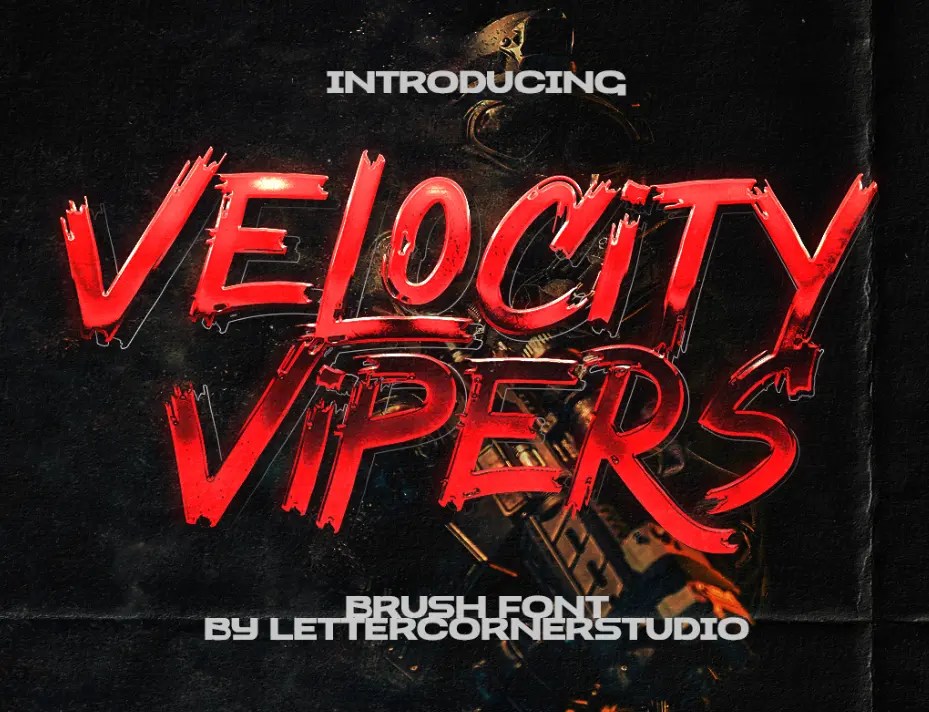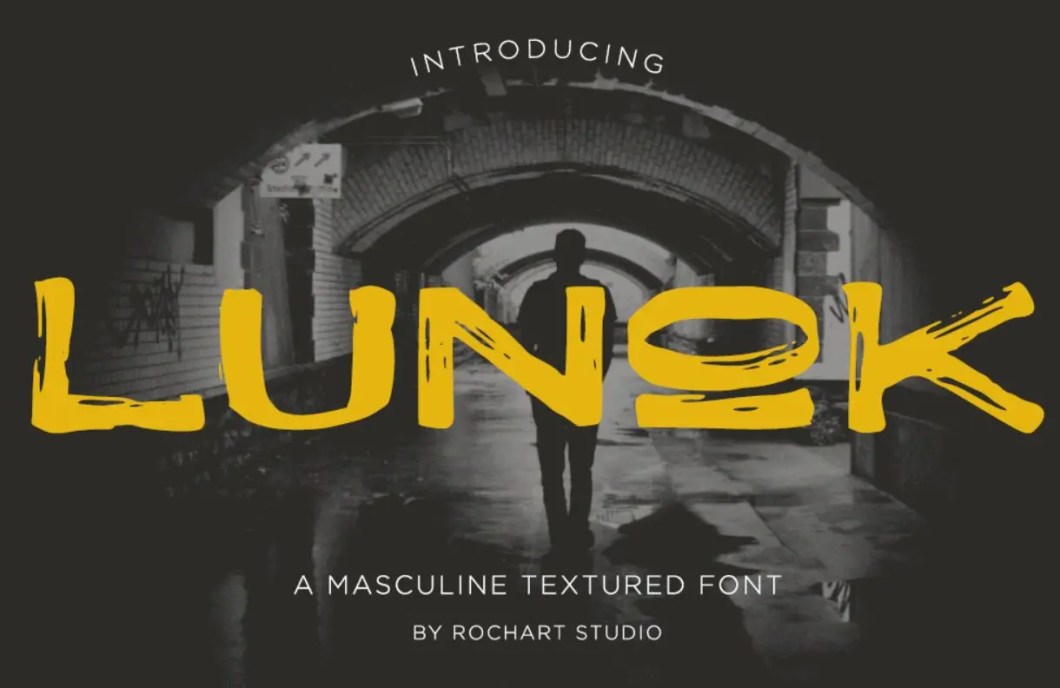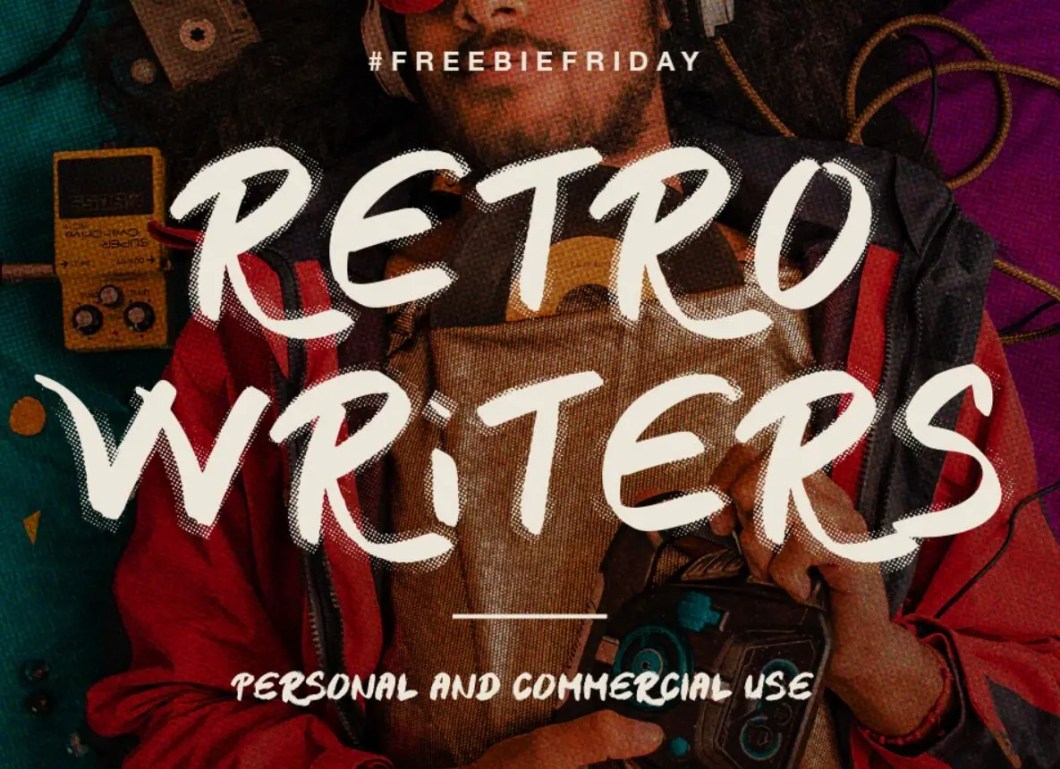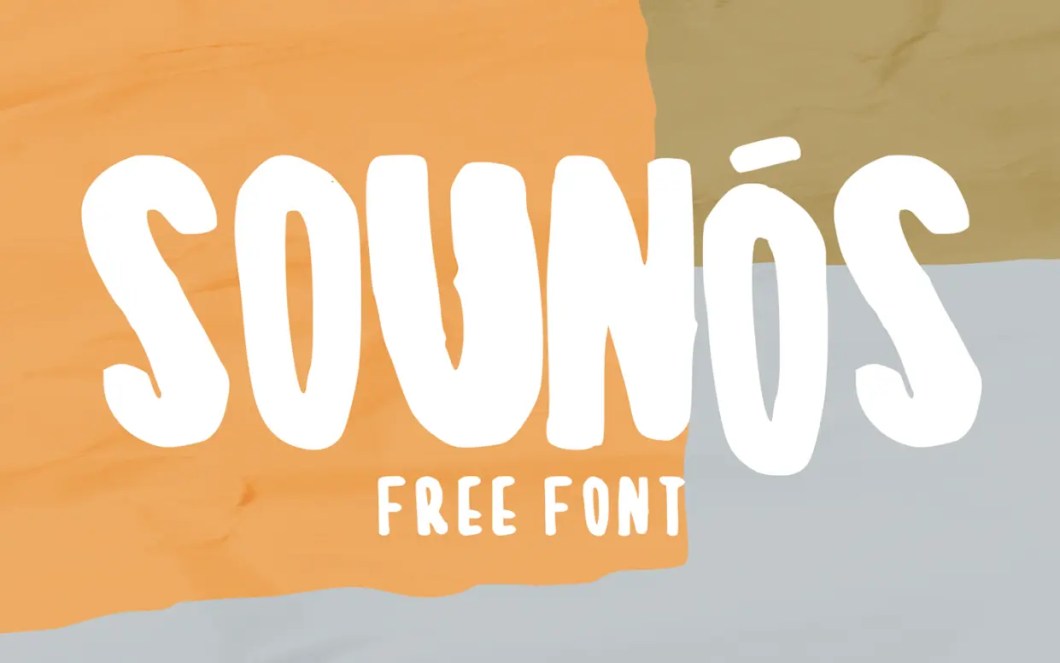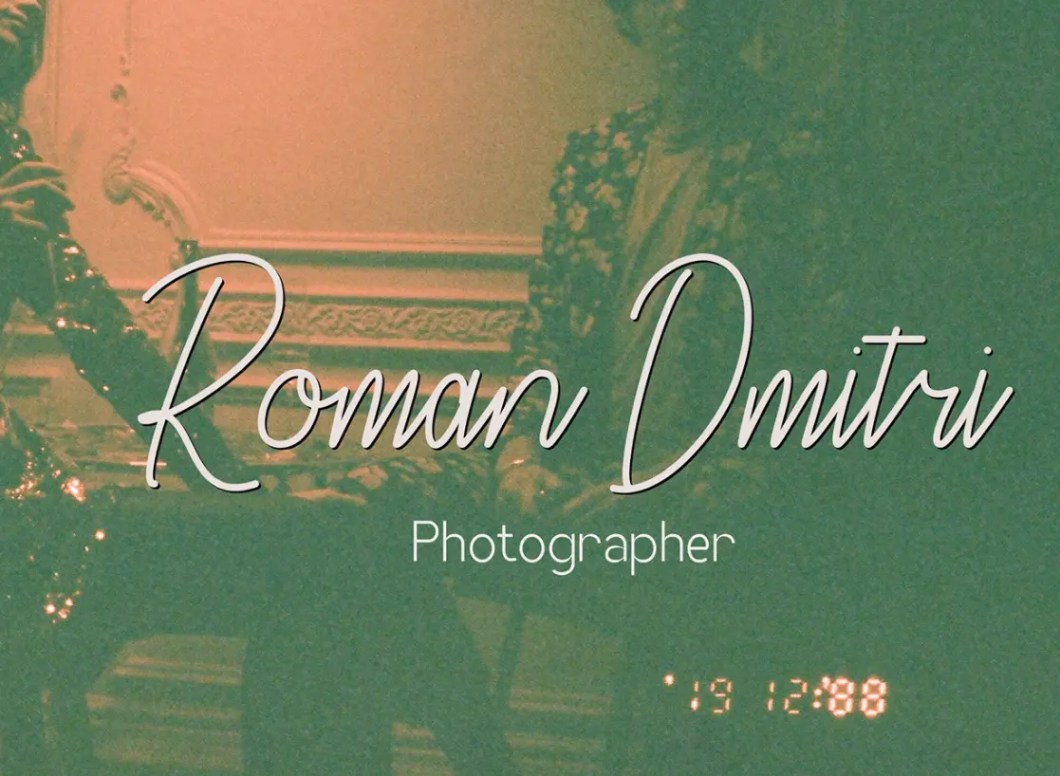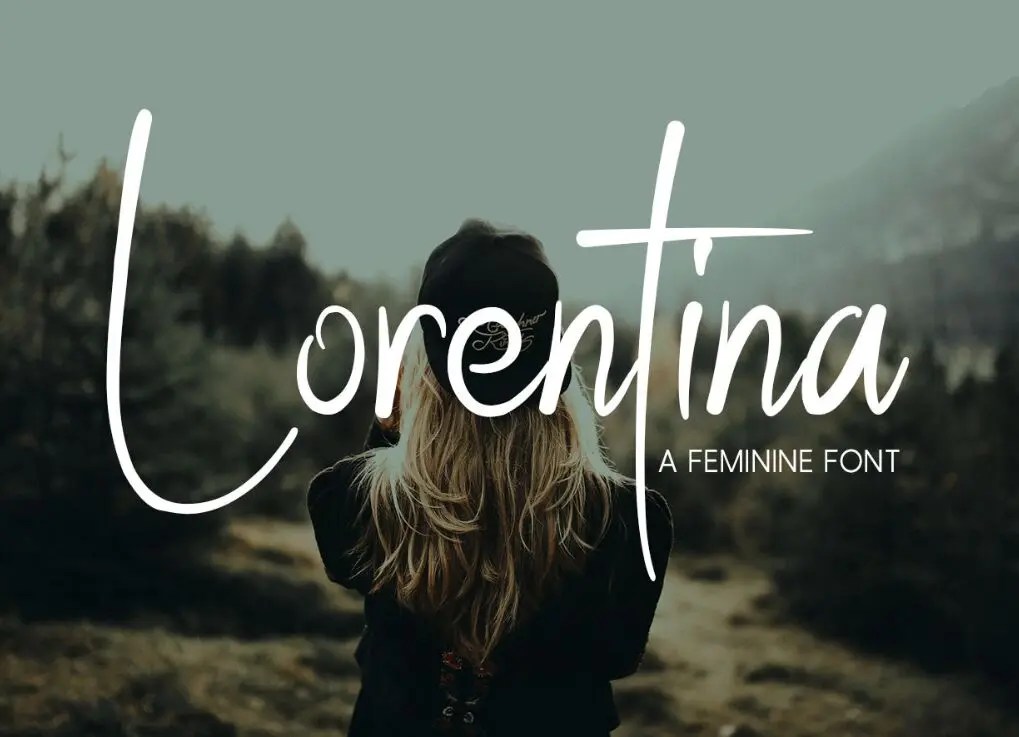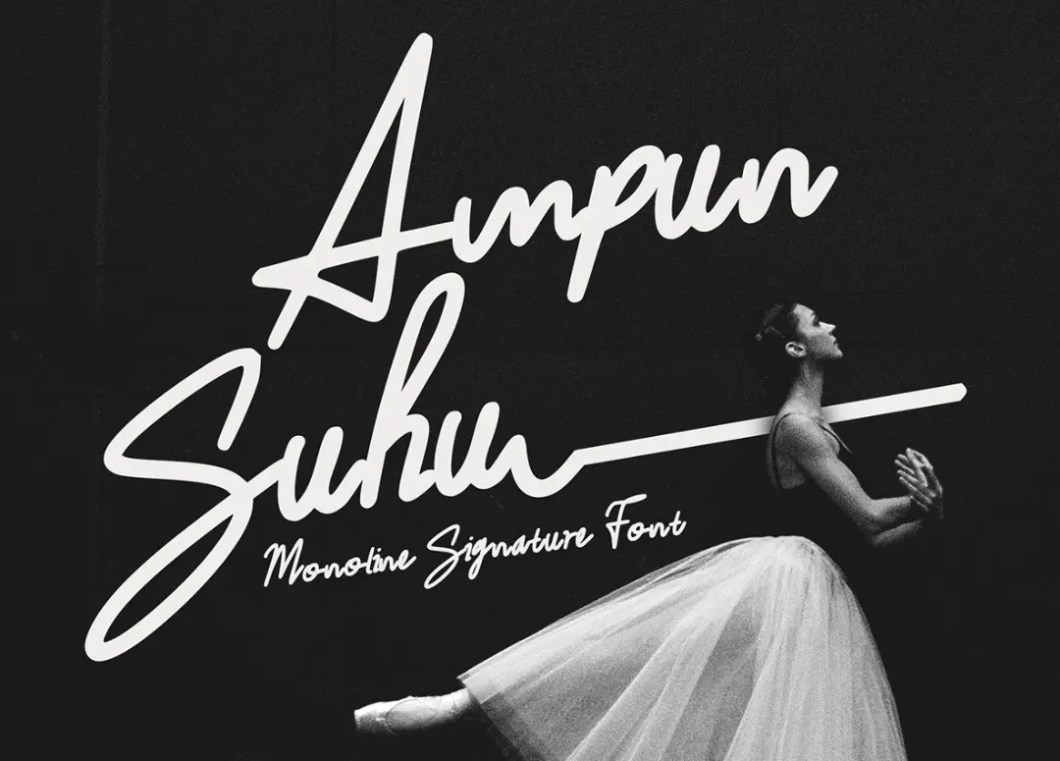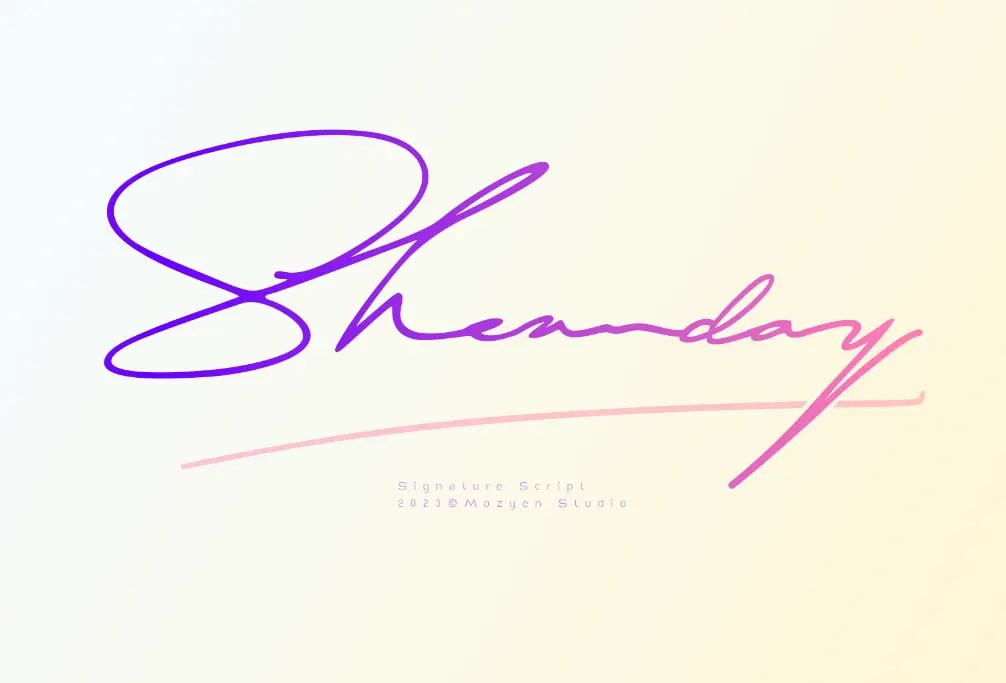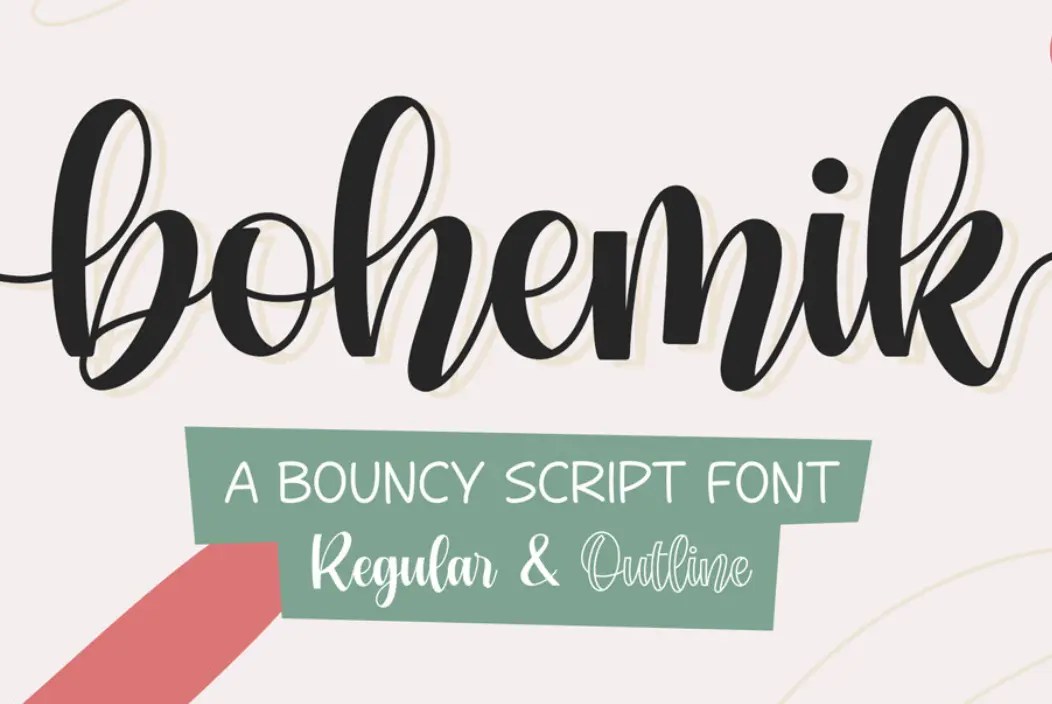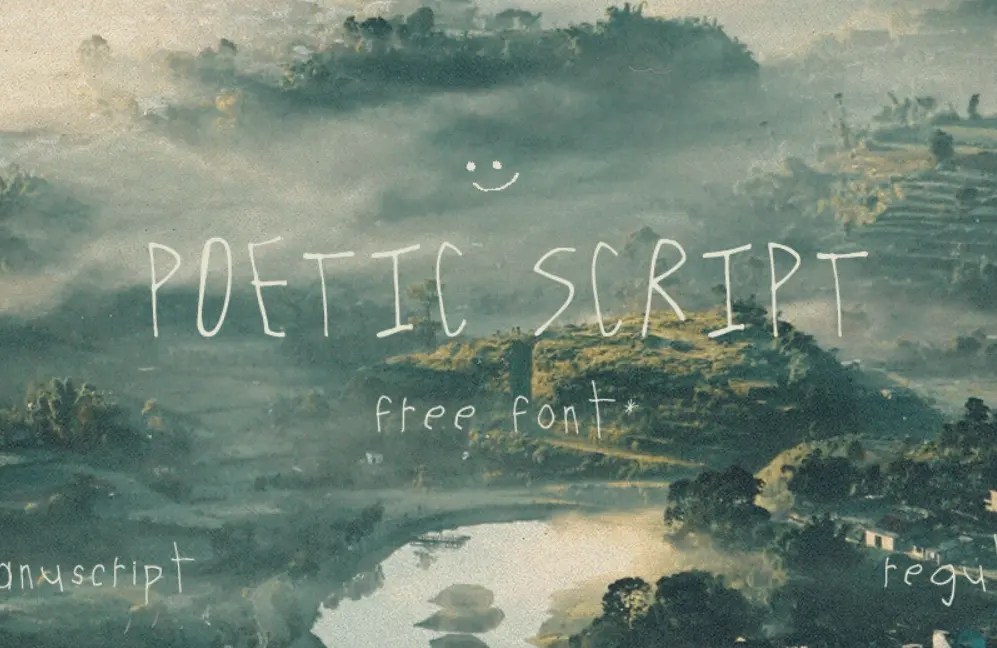
80+ beste Brush/Script/Calligraphy/Signature Fonts für modernes Grafikdesign
Die Brush Script-Schriftart ist eine äußerst vielseitige Schriftart, die in zahlreichen Designprojekten Anwendung findet. Mit einer reichen Geschichte, die bis zu ihrer Einführung im Jahr 1942 durch den amerikanischen Schriftenentwerfer Robert E. Smith zurückreicht, erlangte die Brush Script in den 1960er Jahren immense Popularität und wurde zu einem festen Bestandteil von Werbung und Promotionmaterialien der Nachkriegszeit.
Bekannte Logos, die diese Schriftart verwenden, sind möglicherweise im „The Price is Right“-Spiel in der „One Away“-Runde, im ursprünglichen Logo der Jerry Springer Show und im Logo von Virtua Fighter zu finden.
Obwohl diese Art von Schrift in Logos möglicherweise nicht so häufig vorkommt, ist sie eine der am häufigsten verwendeten Schriftarten für informelle Skripte. Ihre weitverbreitete Verwendung im Webdesign wird auf ihre Beliebtheit, Lesbarkeit und nostalgische Ästhetik zurückgeführt.
Der Vintage-Charme von Brush Script liegt in seinem handgeschriebenen, informellen Stil – eine Abkehr von den digitalen Schriftarten, die in der heutigen Designlandschaft vorherrschen. In einer Ära, die von digitalen Werkzeugen dominiert wird, wird der Reiz einer Schrift, die an handgefertigte Federn, Kalligrafie und Malerei erinnert, zunehmend geschätzt.
Die Wiederbelebung von Brush Script-Schriftarten deutet auf einen wachsenden Trend hin. Es ist daher für Designer entscheidend, eine vielfältige Sammlung dieser Schriftarten für zukünftige Webdesign-, Logodesign- und Printdesign-Anforderungen zu haben. Um Ihnen dabei zu helfen, habe ich eine Liste der neuesten und besten Brush- und Script-Schriftarten im Internet zusammengestellt.
Brush Fonts:
SUPERNOVA Brush Font
VELOCITY VIPERS Brush Font
SOUNÓS Font
Brushelva Font
RETRO WRITERS
RETRO WRITERS Free Grunge Display Font
Better Brush Font
Lunok Font
Chi Free Handwritten Font
Griffin Brush Font
Vegabond FREE Brush Font
Maylani Free Handwritten Font
Hot Ink Free Font
Buttergone Brush Font
Ikigai Free Handwritten Font
Hallyeet Font
Tracker Font
Yokai Rough Brush Font
Taki Taki Brush Font
Hiatus Free Font
AlphaBee Free Display Font
Going Under Free Font
HUF FREE FONT
Oliver Blush Calligraphy Modern Font
Samoell Free Font
Rehat Free Font
Paintbrush Font
PROTEST Brush Font
MALER Font
Backpacker
Dexotick
Valden Brush Font
Kulan Free Font
Oh Now Brush Font
Free White Christmas SVG font
THRONE – SVG and regular OTF font
THRONE - SVG and regular OTF font
Stiverx Brush Script
Fake Serif Font
Welcome 2019 Font
UPIRDRY WATER-BRUSH FONT
Big Snow Free Font
Rogeu Brush
Rogeu Brush is 100% free for personal use and commercial project.
Rogeu Brush
Herupzor Typeface
Oyget Brush Font
Oyget Brush Font-min
Larries Font
UStroke Free Font
UNDERBRIDGE WET FONT
UNDERBRIDGE WET FONT-min
HANDWRITTEN Typeface
Abuget Brush Font
Odachi – Free Brush Font
Odachi is completely free for all commercial purposes.You don’t need a license to use it in commercial projects.
Odachi Brush Font
Sunshine Reggae Lowercase Font
MR. GRIEVES | Free Typeface
MR. GRIEVES Free Typeface
Paint the Sky Free Brush Font
Bahagia Typeface
Free Font Balloon
Espa Free Brush Font
OCEAN SIX – FREE BRUSH FONT
OCEAN SIX - FREE BRUSH FONT
Balmy – Free Brush Font
Balmy - Free Brush Font
Eufoniem | Free Font